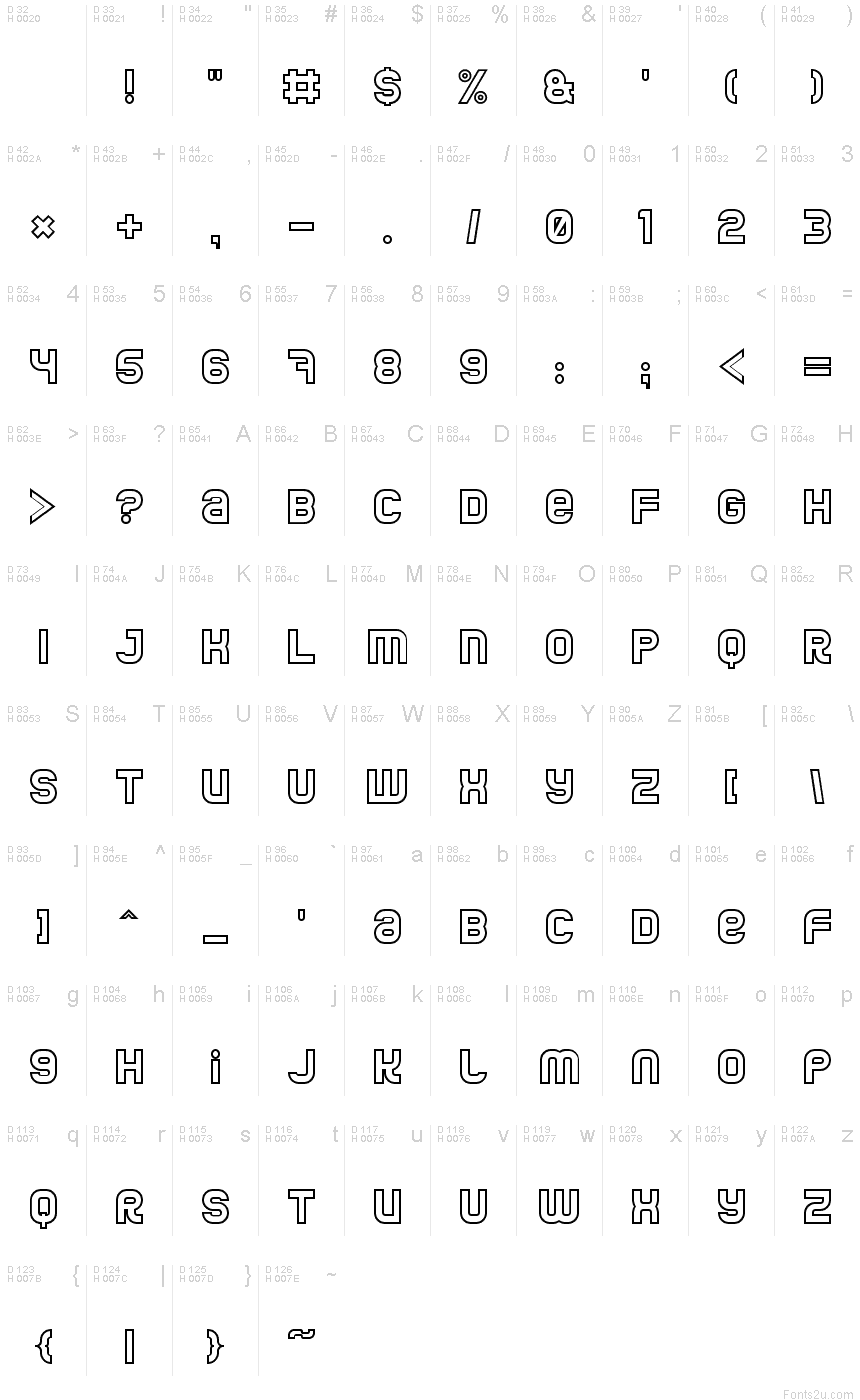
Jumbo Outline
Jumbo Outline od Dustbust Fonts je bezplatné dekorativní bezpatkové písmo. Jeho silná, zaoblená kostra obepnutá čistým dvojitým obrysem dodává každému slovu výrazný, „nafukovací“ dojem – jako neonové trubice nebo nadýchané nápisy psané fixou. Písmena jsou široká, přátelská a mají rovnoměrné rozestupy, takže zůstávají čitelná i při velkých velikostech, přičemž si stále zachovávají svůj zábavný a nepřehlédnutelný vzhled.
S Jumbo Outline získají vaše nadpisy okamžitě hravý, karnevalový nádech, který upoutá pozornost, aniž by působil rušivě. Toto bezplatné písmo skvěle vynikne na plakátech, obalech hraček či dětských produktů, pozvánkách na párty, výrazných webových nadpisech, samolepkách a reklamní grafice. Pro snadné párování použijte Jumbo Outline na hlavní nadpisy a doplňte jej jednoduchým geometrickým bezpatkovým písmem pro doprovodný text v menších velikostech.